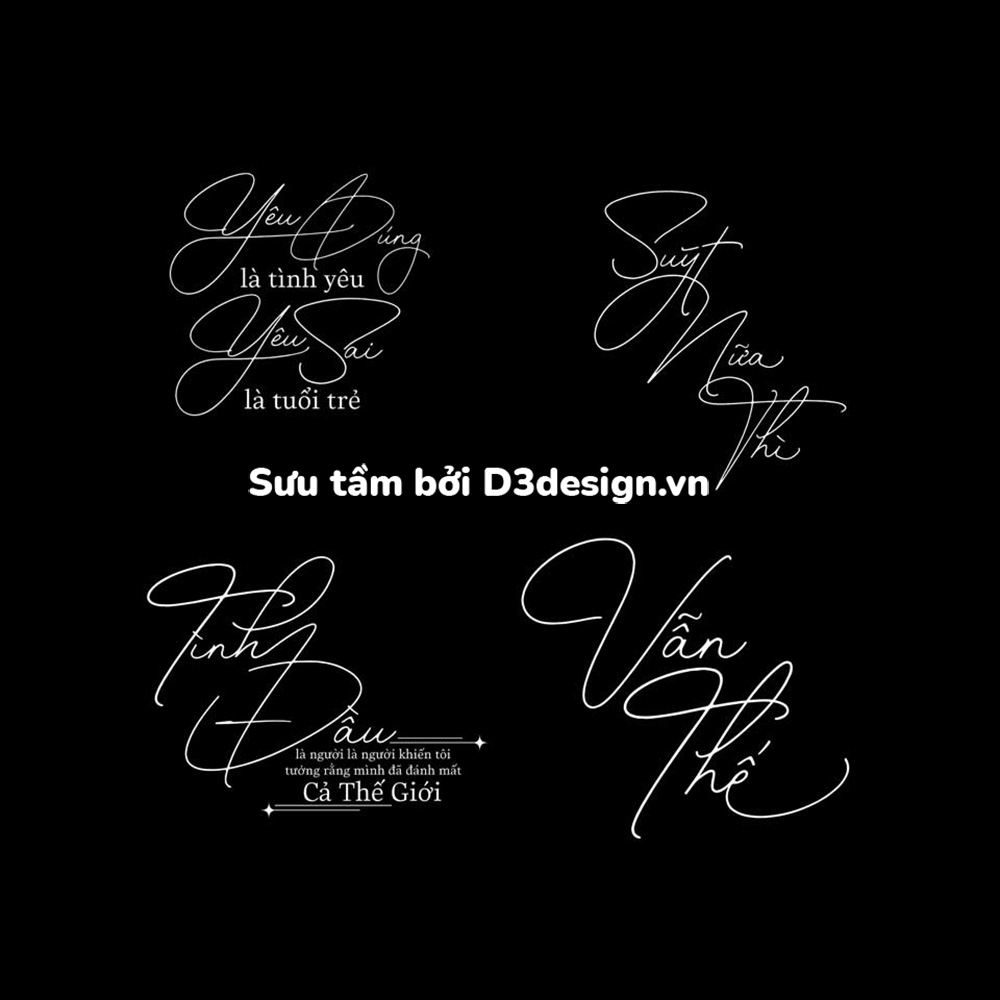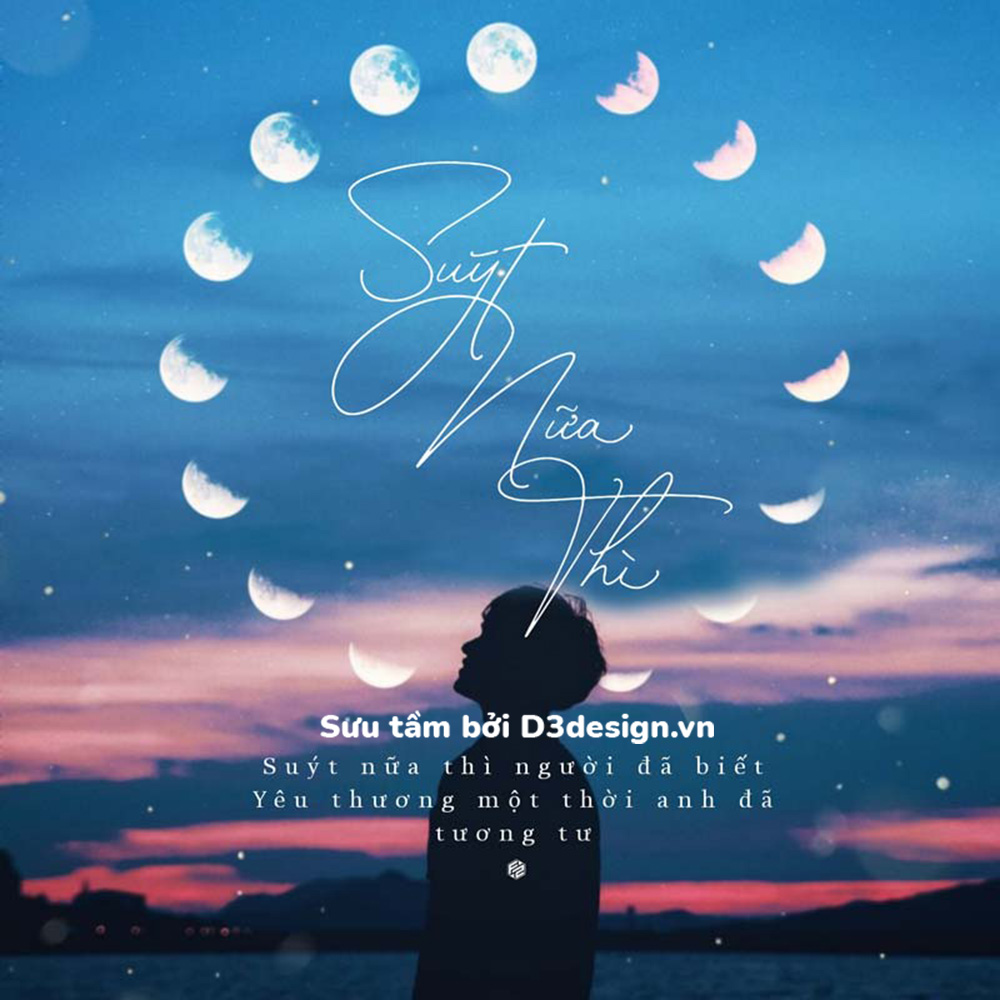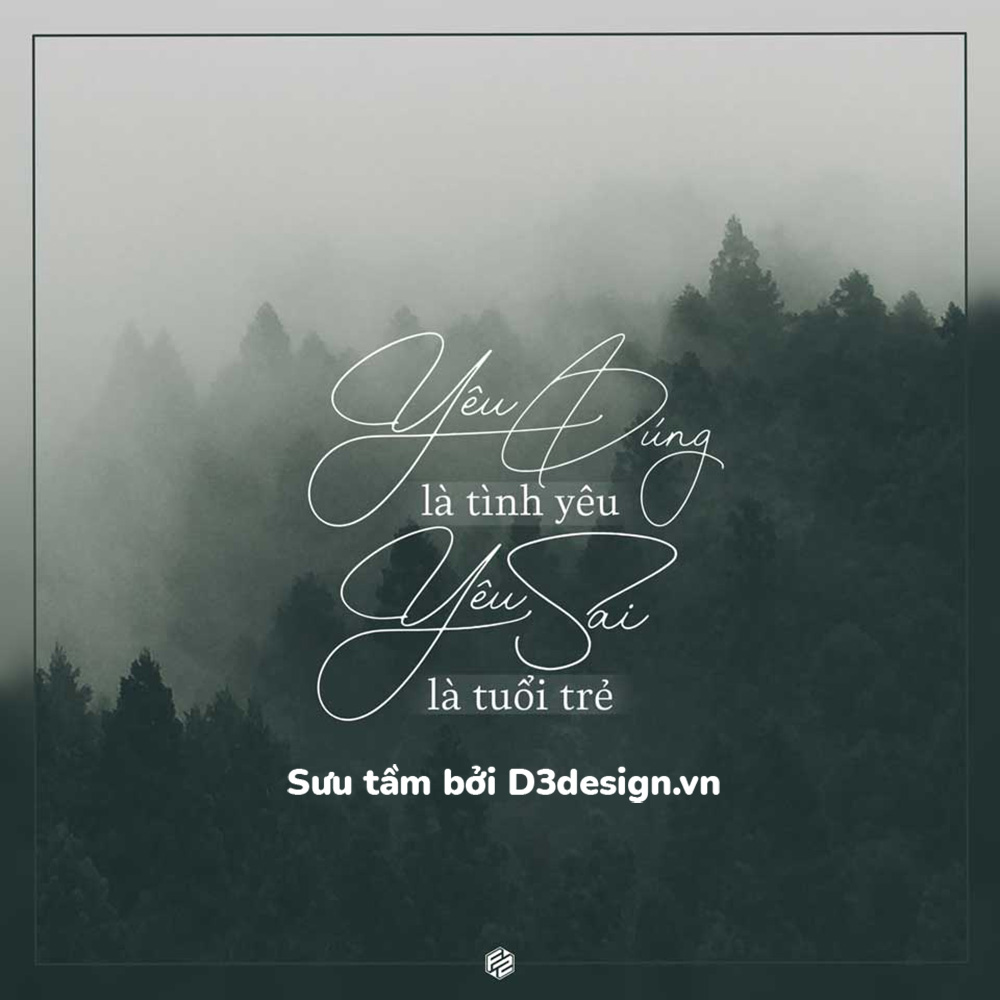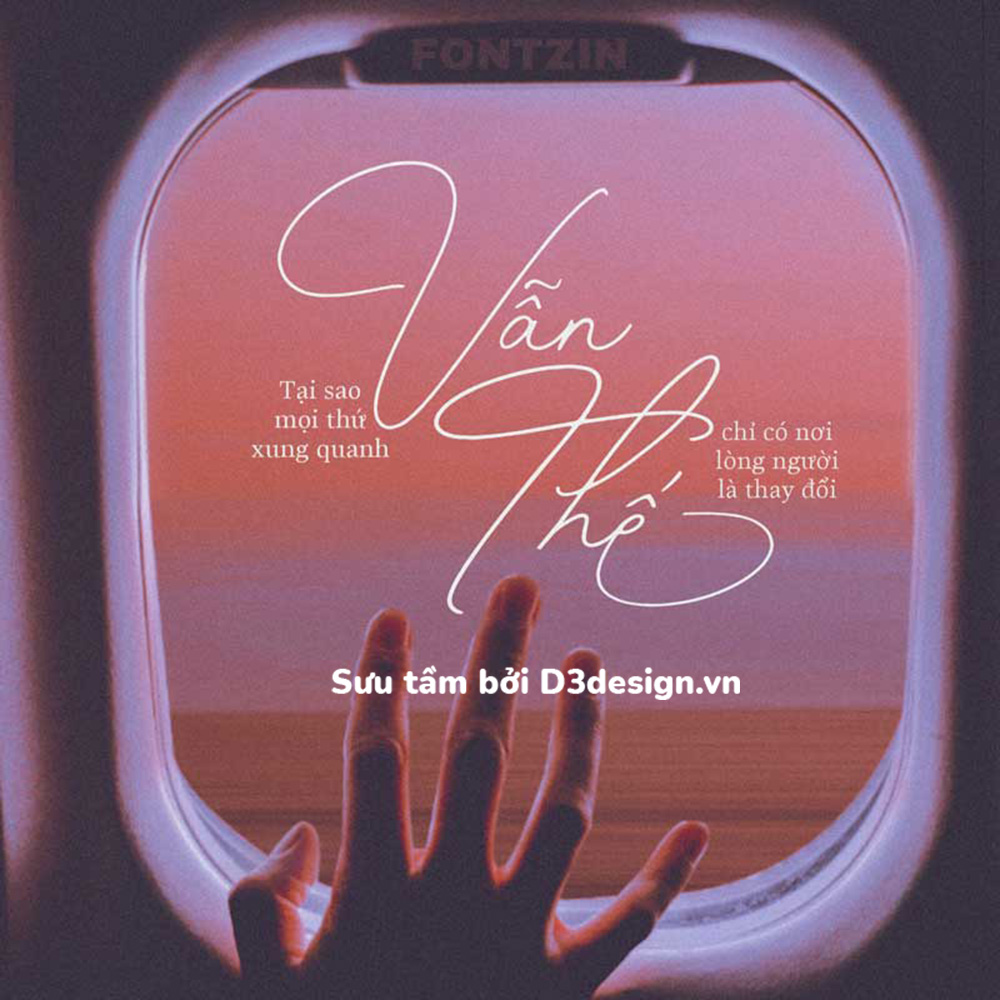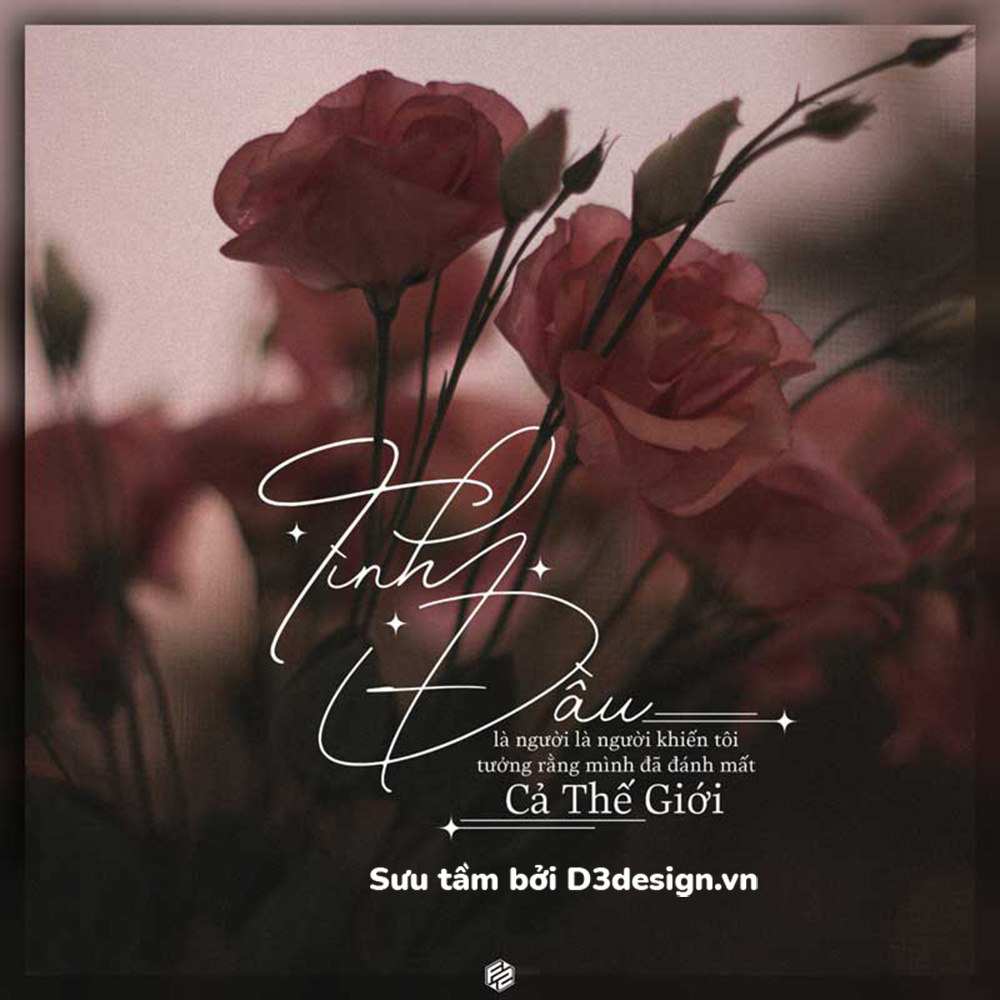
Font Việt Hóa - The Handwritten Watermark Font Chữ Ký Siêu Đẹp
Font The Handwritten Watermark Việt hóa xứng đáng là một siêu phẩm font viết tay, nét chữ được cách điệu kết hợp dạng monoline tạo nên sự thu hút kỳ lạ với bộ phông chữ này.
Bộ font này được thiết kế tối giản không có nhiều ký tự thay thế (trong font tác giả có thêm 1 – 2 ký tự thay thế tùy từng chữ) admin Đức Thủy đã thêm quy tắc gõ cho mỗi ký tự bạn có thể thêm số đằng sau để sử dụng.